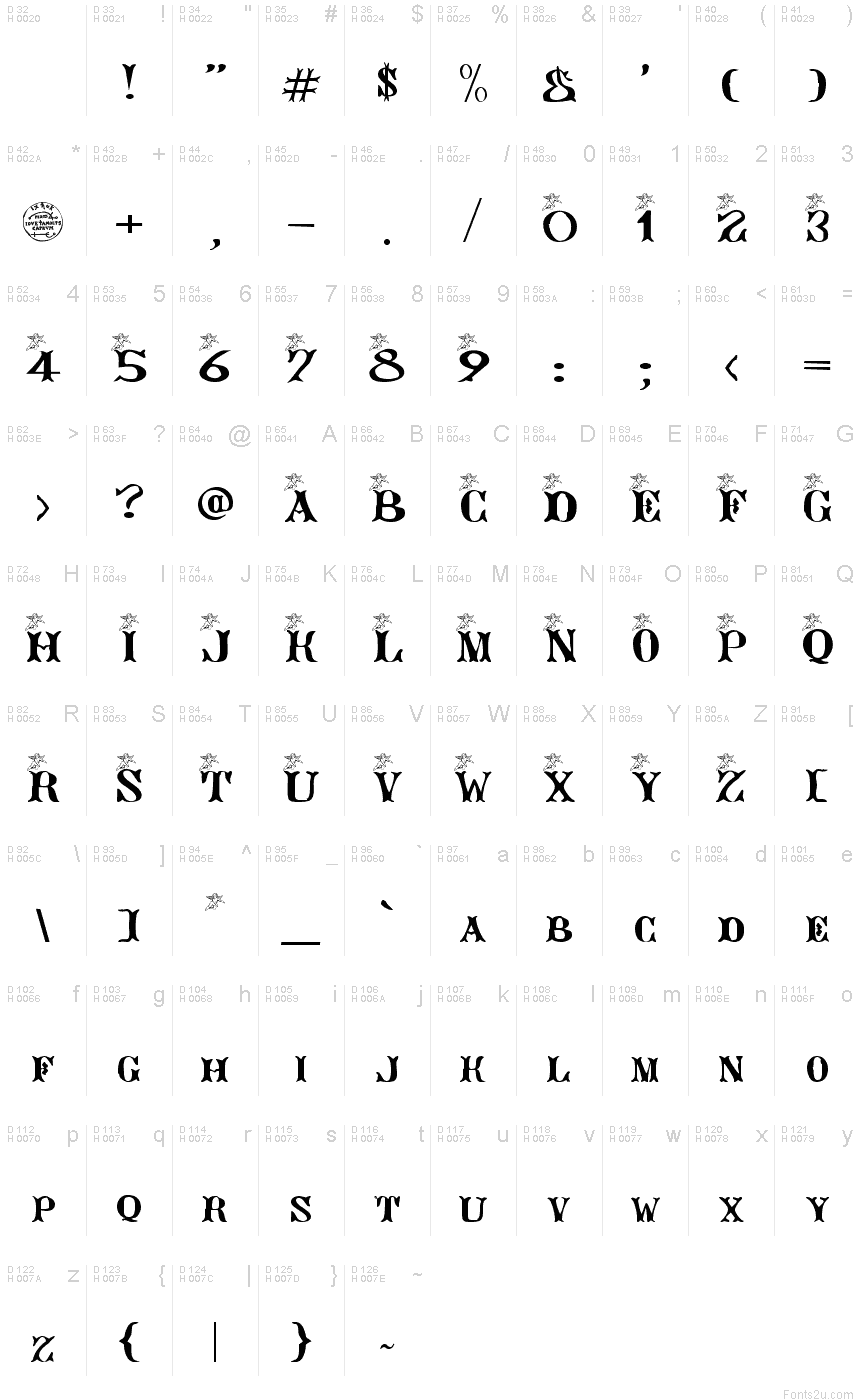
خط Ange Gardien من تصميم Michel Bujardet هو خط زخرفي مجاني من طراز الفانتازيا، يبدو وكأنه خرج للتو من صفحات كتاب قصص مصور. الحروف ذات طابع ثقيل ومحبرة وتتوهج بلمسة قوطية، بينما تضفي الملائكة الحارسة الصغيرة المتمركزة فوق الحروف بريقاً غريباً وروحانياً. يتميز الخط بإيقاع جريء وثابت، مما يضفي على كلماتك طابعاً احتفالياً دون أن يبدو متصلباً أو قديماً.
باستخدام Ange Gardien، تكتسب العناوين لمسة من السحر على الفور، مما يجعل هذا الخط المجاني خياراً طبيعياً لأغلفة الكتب، وملصقات الفعاليات الغامضة، ومجموعات التاروت أو العرافة، وملصقات الشموع والصيدليات، وقوائم مطاعم ذات طابع خاص، والشعارات المستوحاة من الطراز القوطي. يتألق الخط بشكل خاص عند استخدامه بأحجام كبيرة حيث تظهر تفاصيل الملائكة بوضوح؛ قم بمطابقته مع خط "سان سيريف" (بلا زوائد) نظيف وخفيف للنص الأساسي للحفاظ على سهولة القراءة والسماح للحروف المزخرفة بسرد القصة.